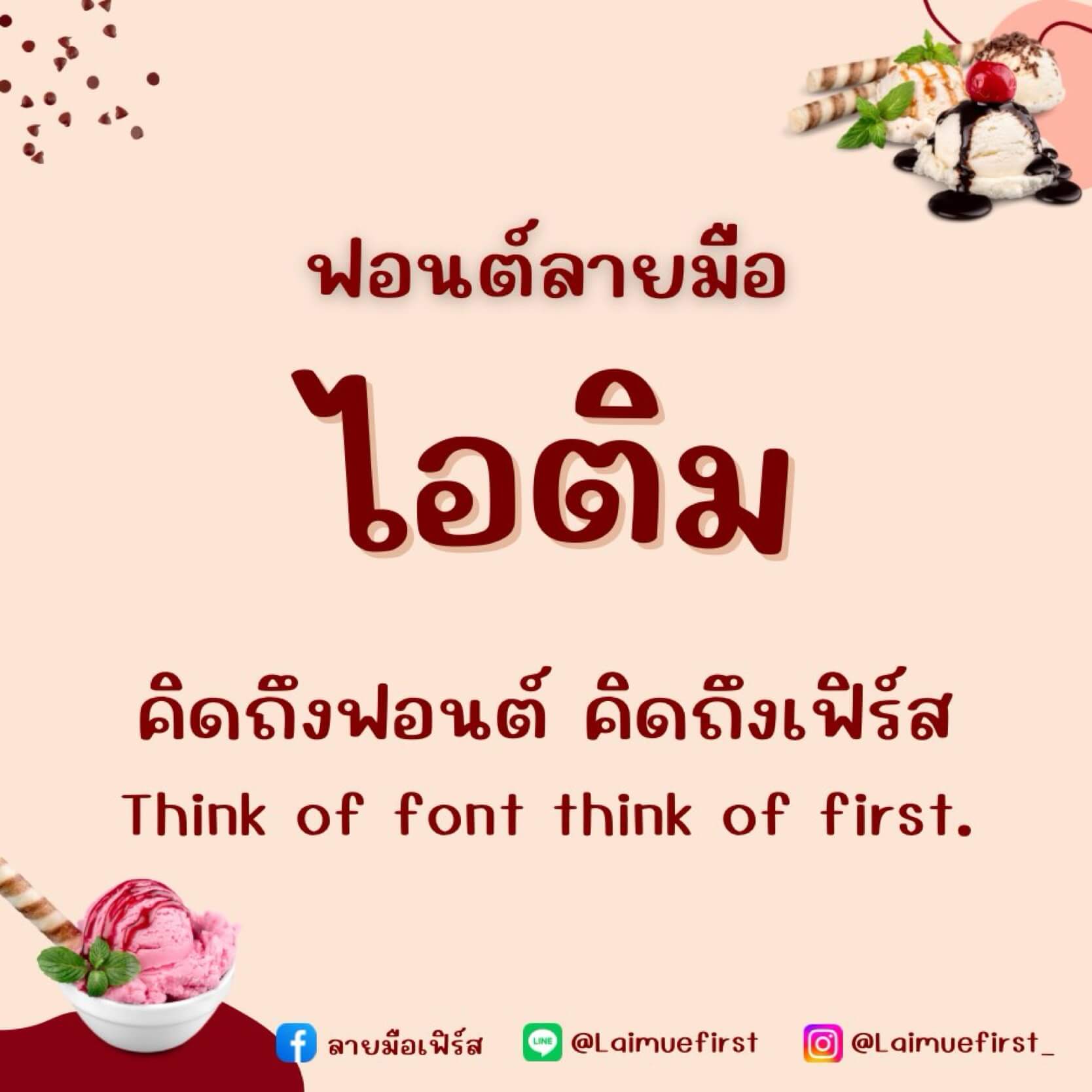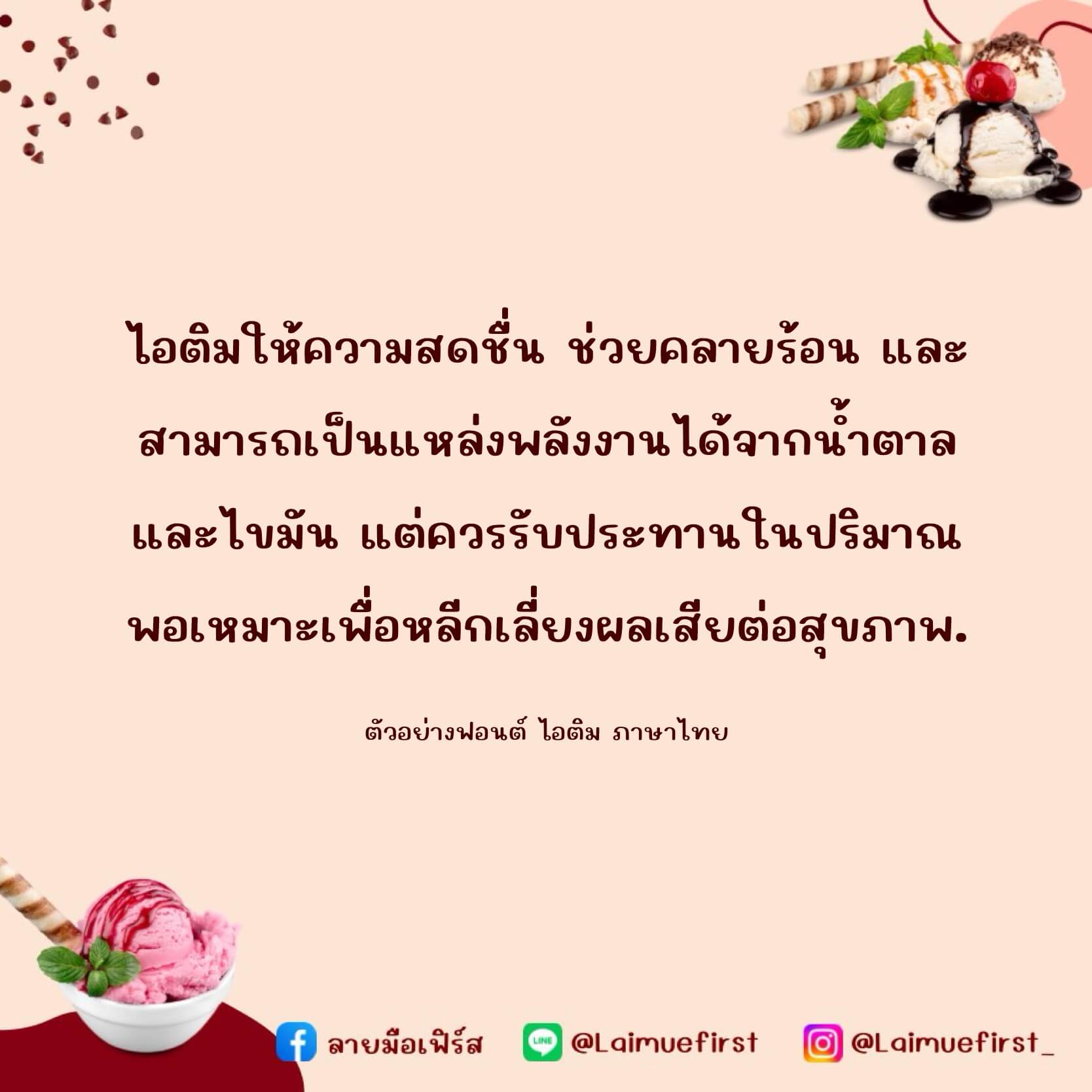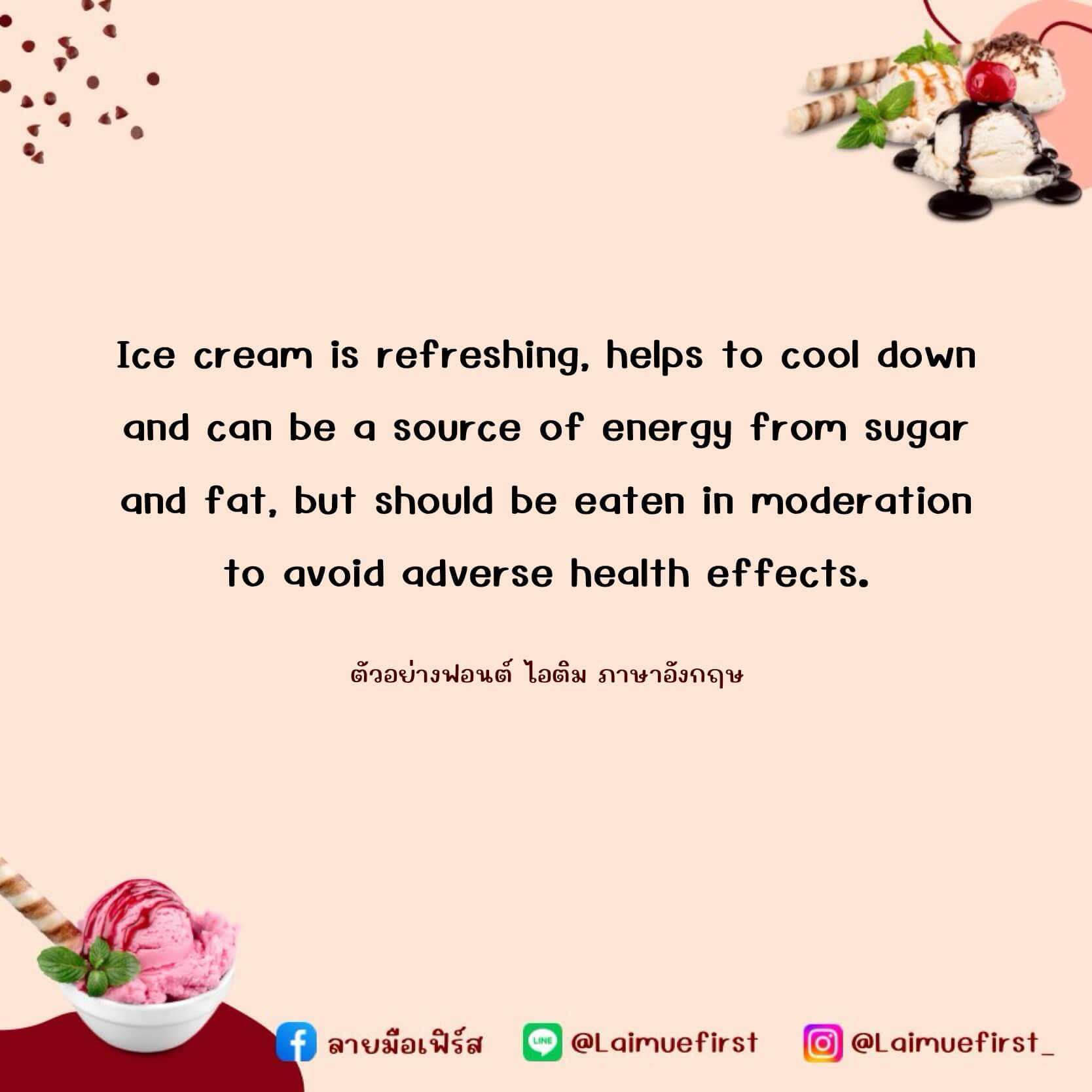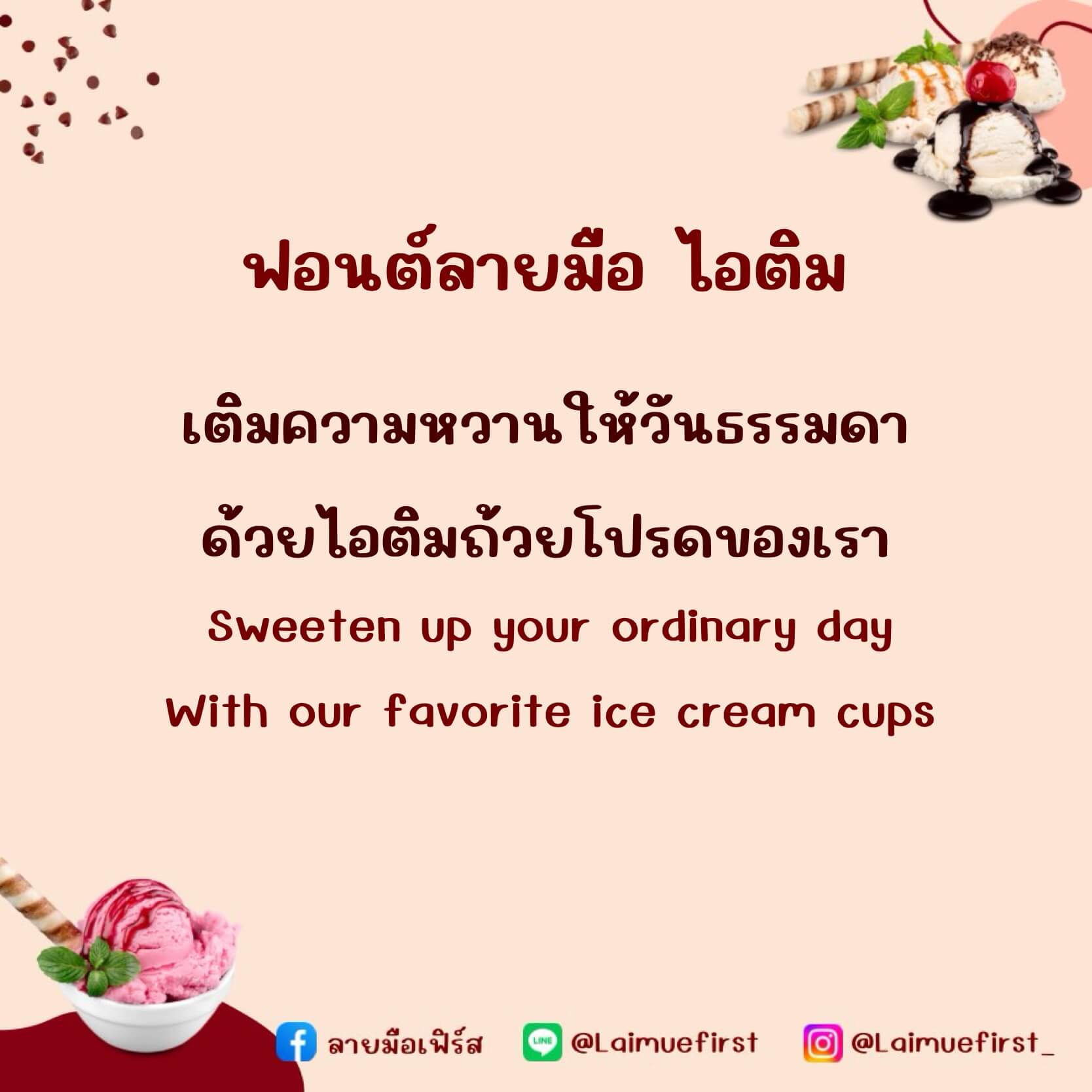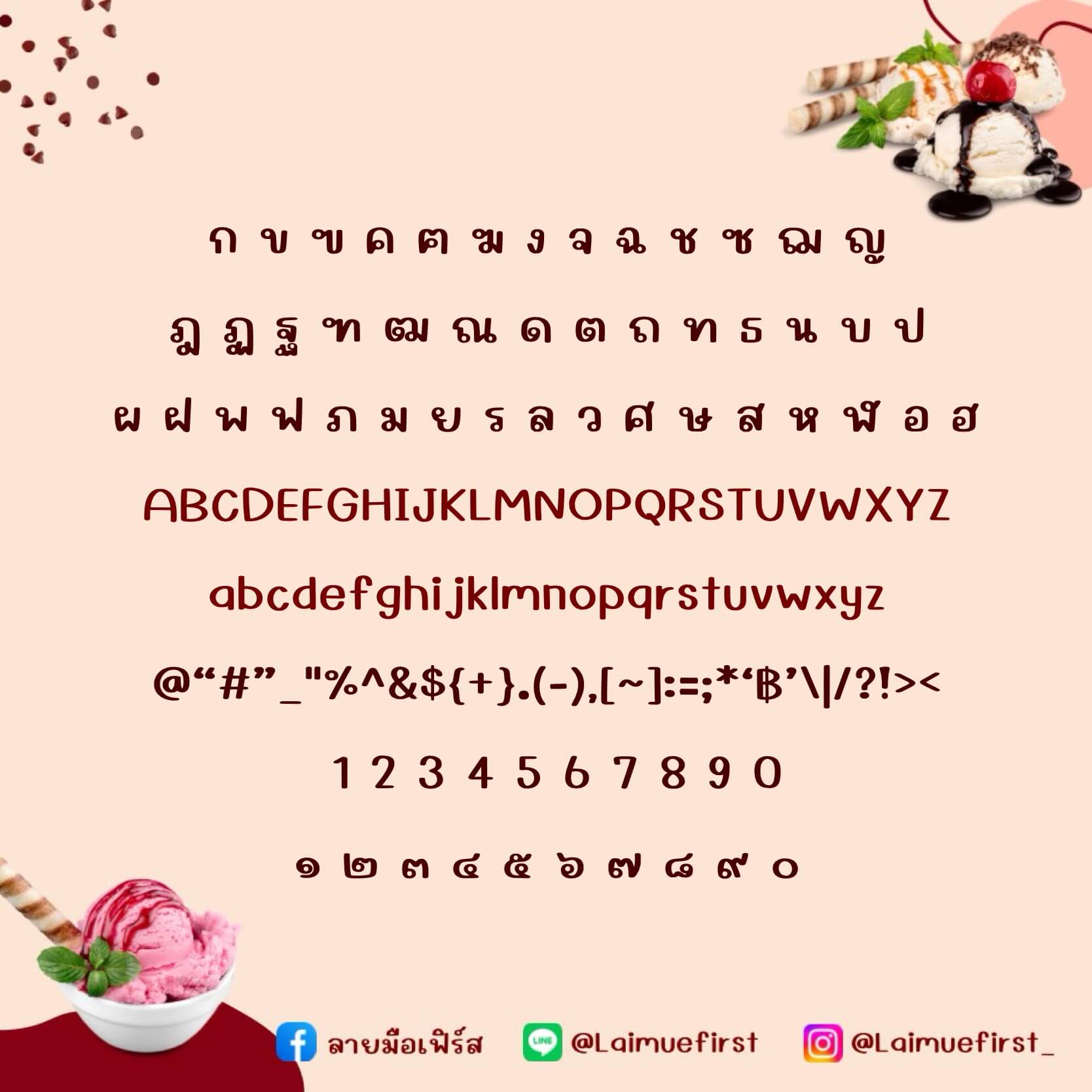
ไอติม (LMF Itim)
ฟอนต์ลายมือ ไอติม (LMF Itim) แจกฟรีสำหรับทดลองใช้งานแบบส่วนตัว เวอร์ชันทดลอง (Demo) ตัวอักษรจะมีขนาดหนา-บางไม่เท่ากัน ไฟล์นี้ไม่อนุญาตให้นำไปใช้เชิงพาณิชย์นะค้าบบบ